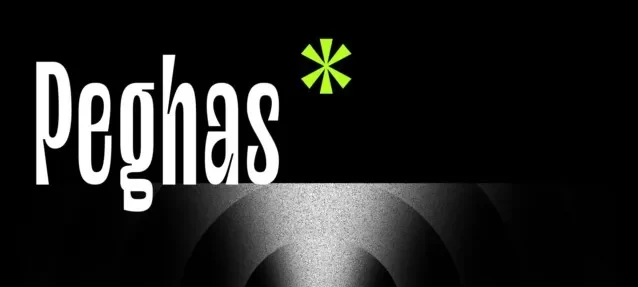
Tác giả: Holyline Design
Font 1FTV Peghas là một font sans serif hiện đại, được thiết kế bởi Holyline Design và thuộc bộ font 1FTV. Font chữ này có phong cách tối giản, đường nét gọn gàng và sắc sảo, phù hợp cho nhiều dự án thiết kế khác nhau: như logo, tiêu đề, thiệp cưới và các tài liệu thương mại. Với độ thanh thoát và khả năng dễ đọc, font 1FTV Peghas đặc biệt hiệu quả khi sử dụng trong các thiết kế cần sự tinh tế nhưng vẫn mạnh mẽ.